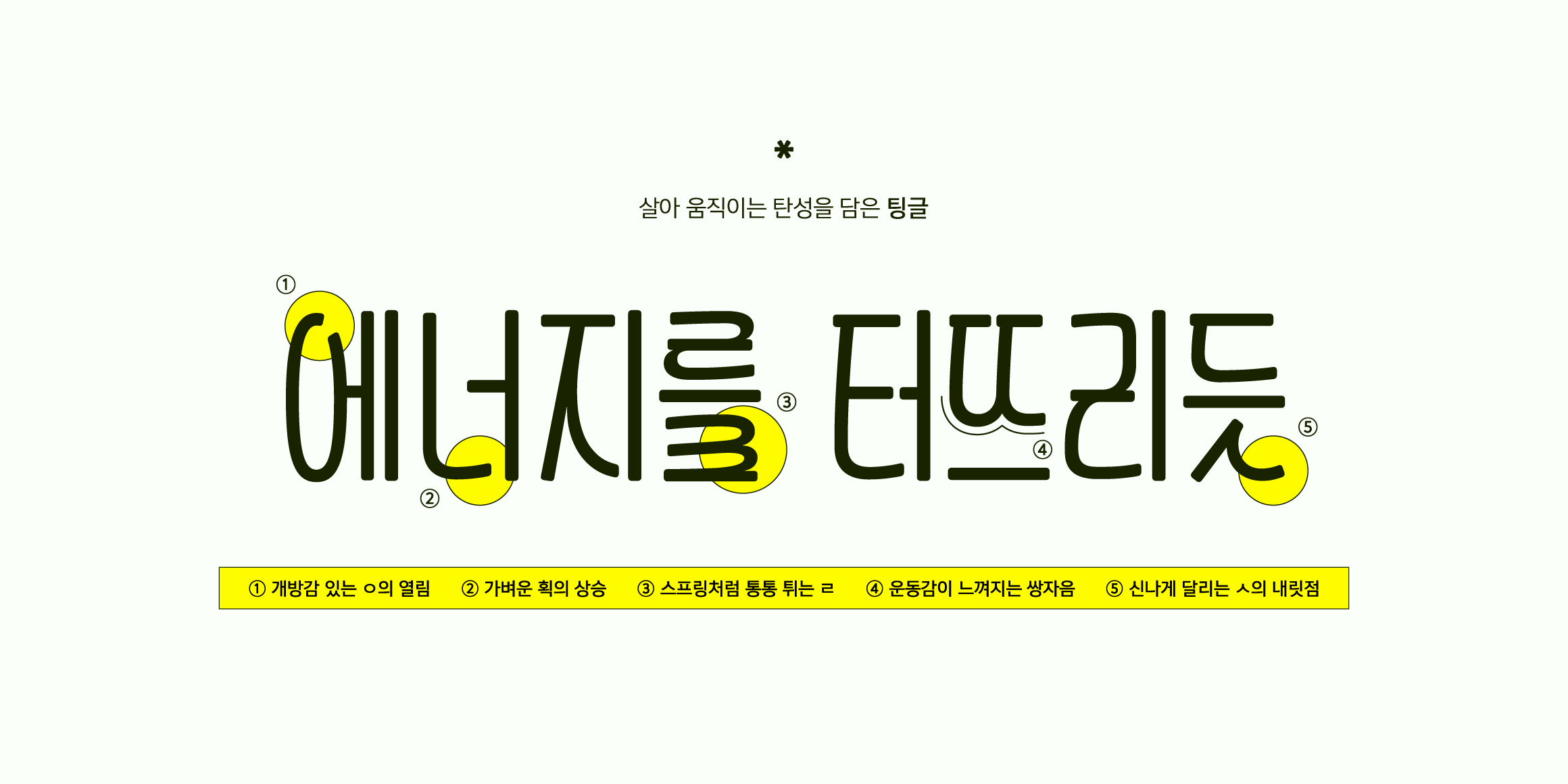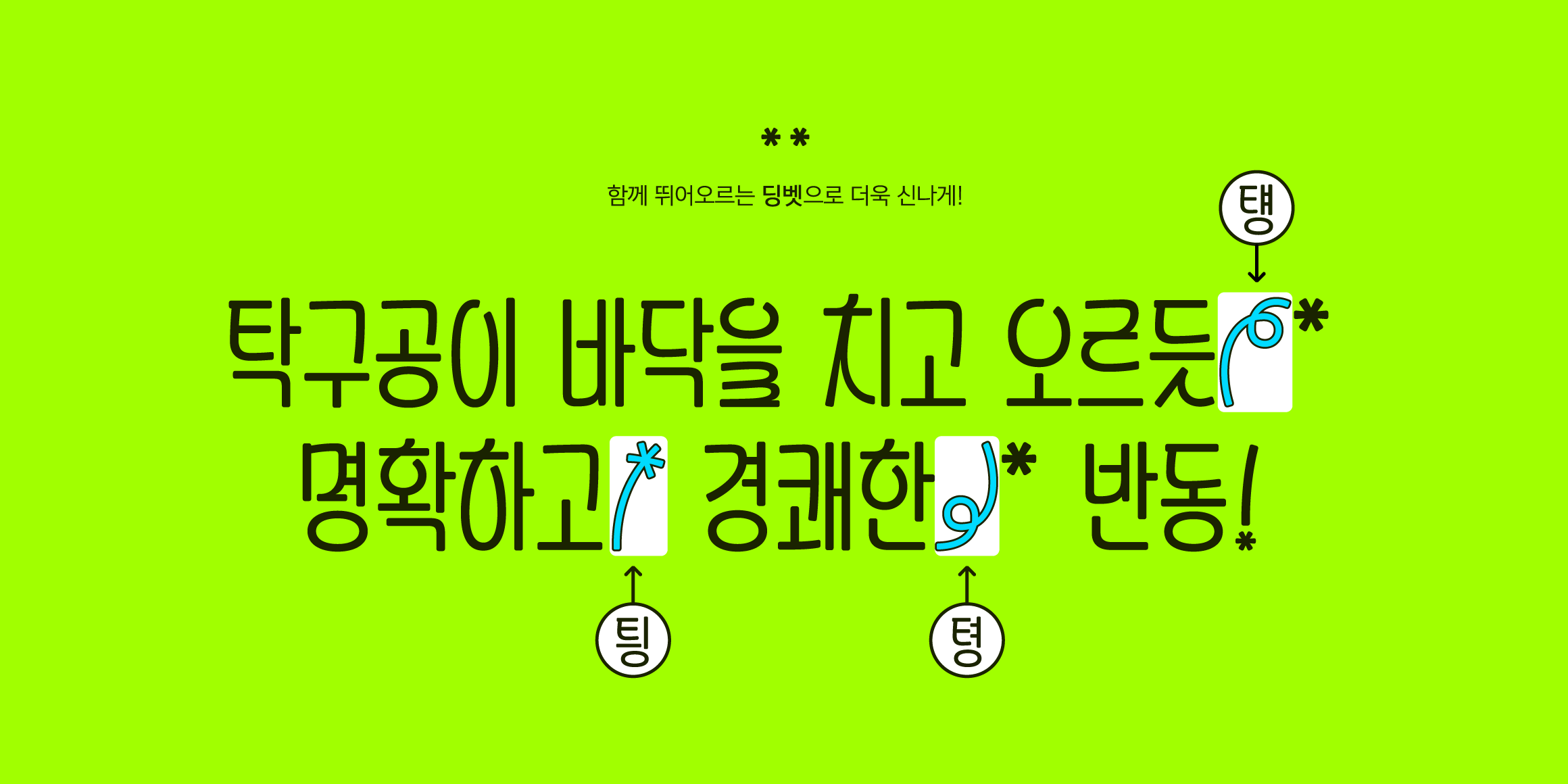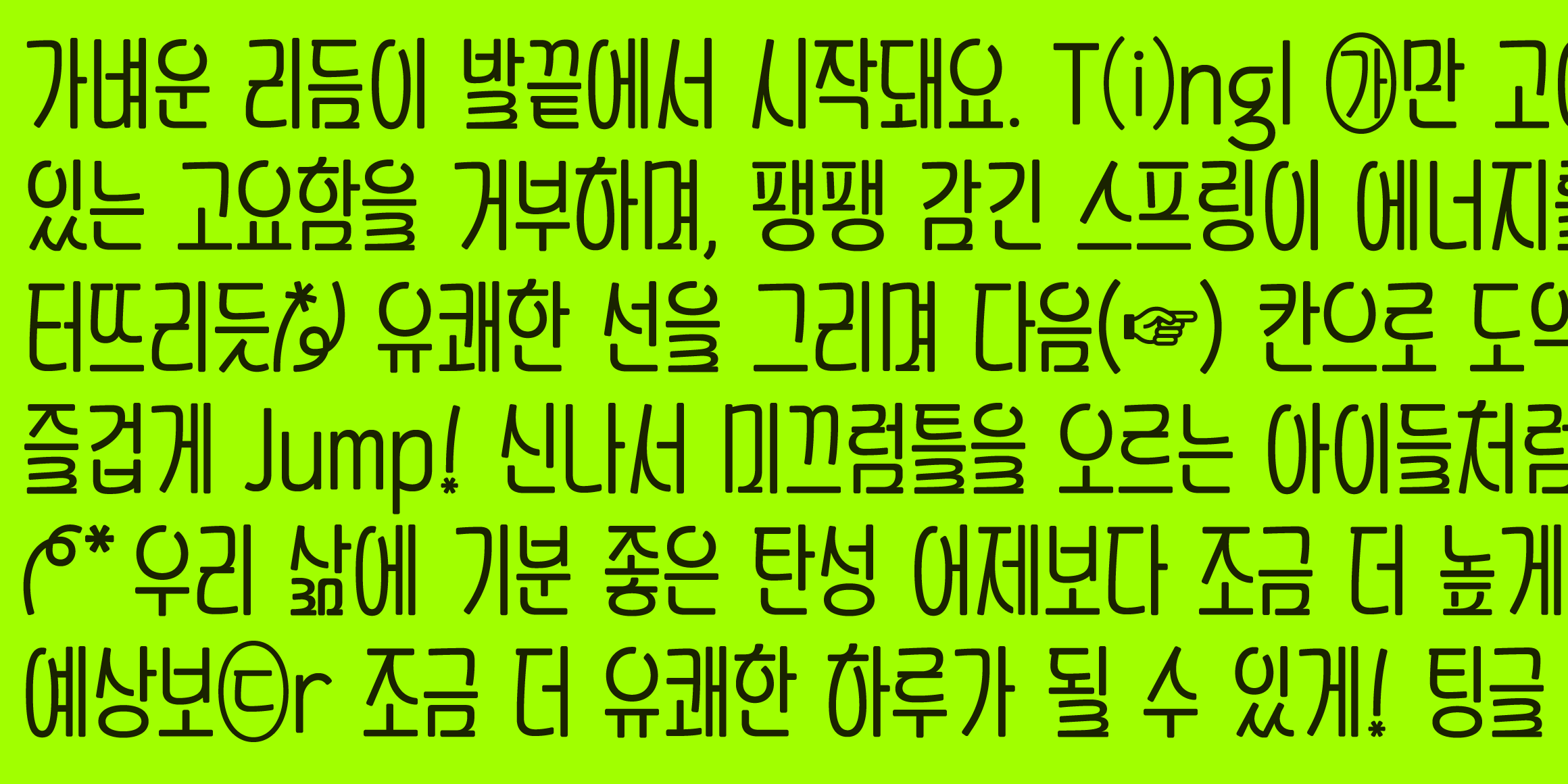
Yoon 팅글
Yoon 팅글은 팽팽하게 감긴 스프링의 탄성을 담아낸 장체 스타일의 서체입니다. 역동적인 곡선들이 끊임없이 이어지며 경쾌한 에너지를 내뿜습니다. 팅글만의 기분 좋은 반동으로 당신의 메시지를 더욱 활기차게 전달해 보세요. ‘틩, 턩, 텽’에 딩벳이 숨어 있습니다.
• 한글 2,780자 / 라틴 95자 / 딩뱃 3자